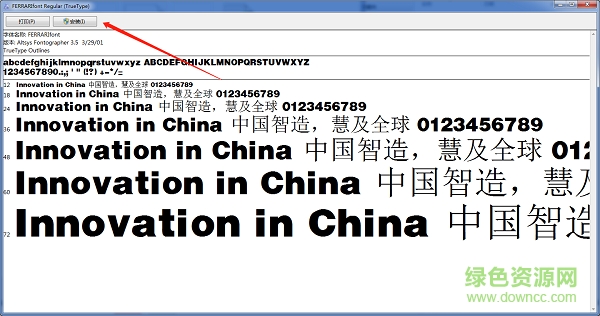
Ferrarifont字體是一款專門為英文打造的排版字體,不同的風(fēng)格能夠帶給用戶更多不同的視覺(jué)體驗(yàn),這款字體更實(shí)用于多個(gè)不同的字體環(huán)境,能夠幫助用戶更好的這里的自己的文章界面,需要的用戶快來(lái)綠色資源網(wǎng)下載吧!
Ferrari英文字體是一款ttf英文字體。大家都知道法拉利吧,而它就是法拉利汽車的字體。另外,這款字體相對(duì)比其他字體來(lái)說(shuō)線條要更加的粗獷,再加上它的線條均為實(shí)線條,所以就會(huì)更加的吸引眼球。